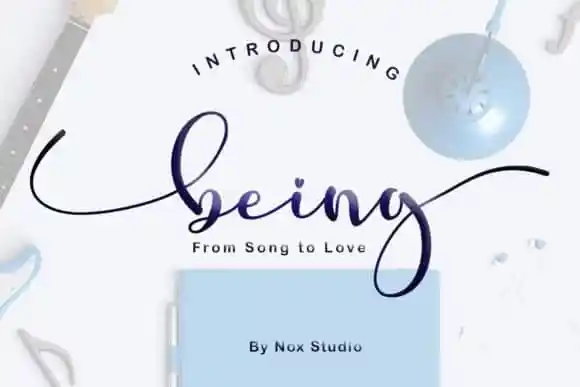
A ‘Being Human Calligraphy Font’ é uma elegante tipografia de script moderna criada pela Nox Studio. Especialmente cuidadosamente elaborada, esta fonte incorpora um toque romântico que transborda do papel. Independentemente do tópico ou projeto em que seja usada, esta font pode transformar qualquer criação num item único e de alta qualidade, tornando-a uma invaluable aquisição para sua biblioteca de fontes. Ideal tanto para os mais sofisticados como para aqueles que desejam um toque romântico, ‘Being Human Calligraphy Font’ é perfeito para adicionar um toque autêntico e especial aos seus projetos de design.